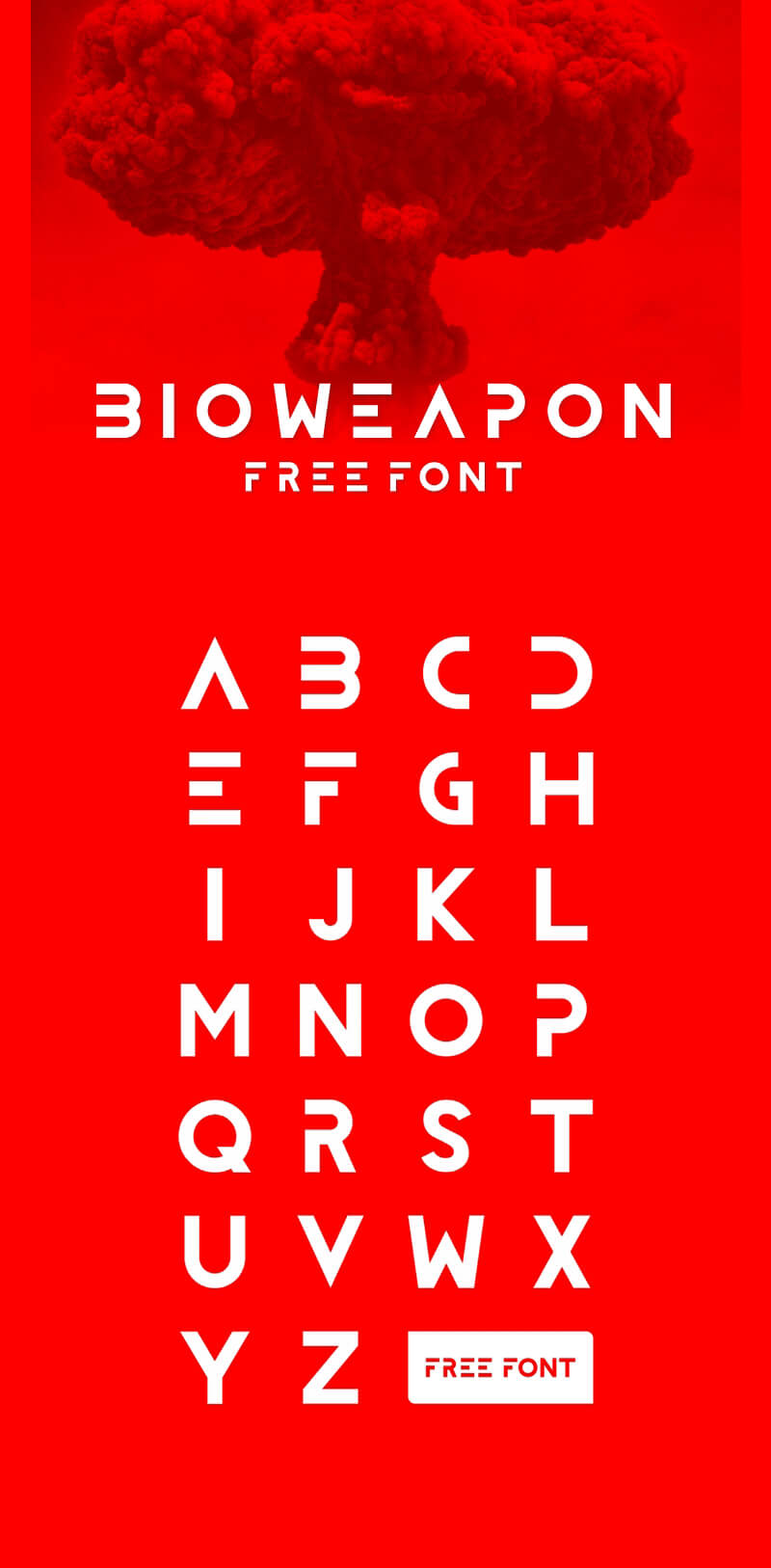
Шрифт - Bioweapon
Этот шрифт был создан под впечатлением от тяжёлых событий с применением биологического оружия в прошлом, которые никогда не будут забыты. Поддержка латиницы.